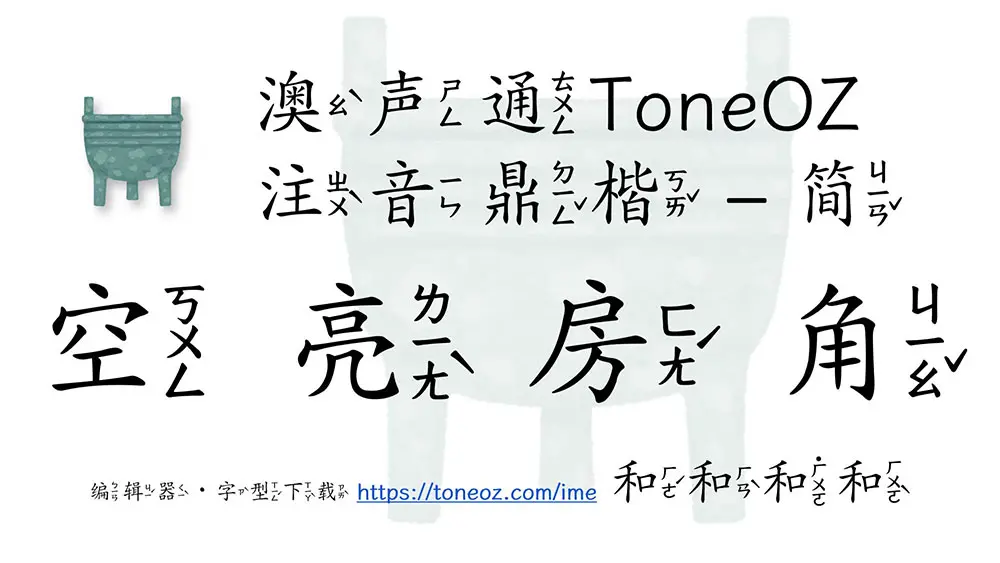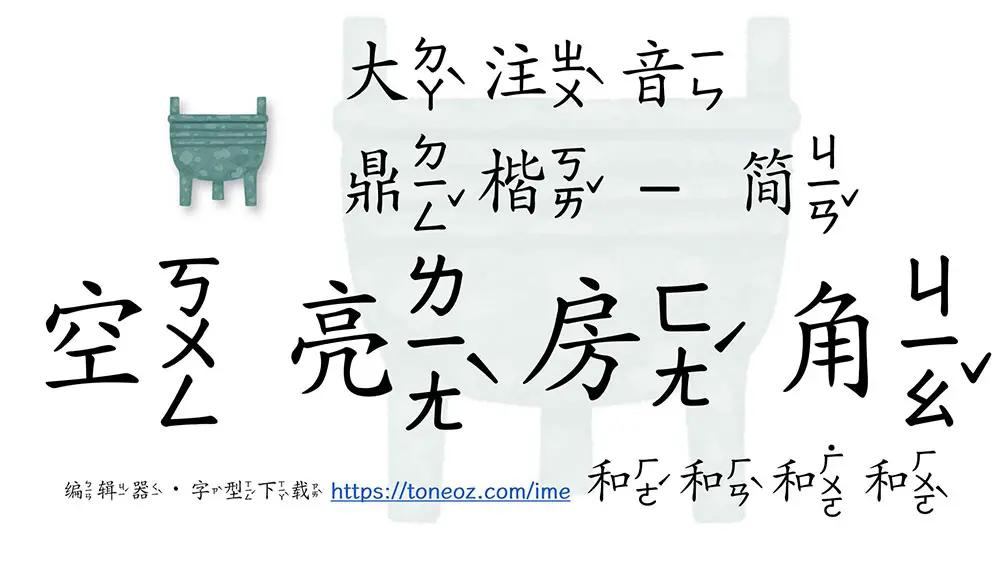
澳聲通注音鼎楷預覽
澳聲通注音鼎楷介紹
澳聲通注音鼎楷是一款基於文鼎PL簡中楷的標準楷體臺灣註釋音字型,免費商用,滿足中文現場教學需求
注意:大注音版的注音很大,適合標題,注音部分可能會與鄰近字重疊,使用時請斟酌搭配字距行距或加上空白使用。
澳聲通小注音鼎楷 ToneOZ-Zhuyin-Kai-Simplified
澳聲通大注音鼎楷 ToneOZ-ZhuyinW-Kai-Simplified